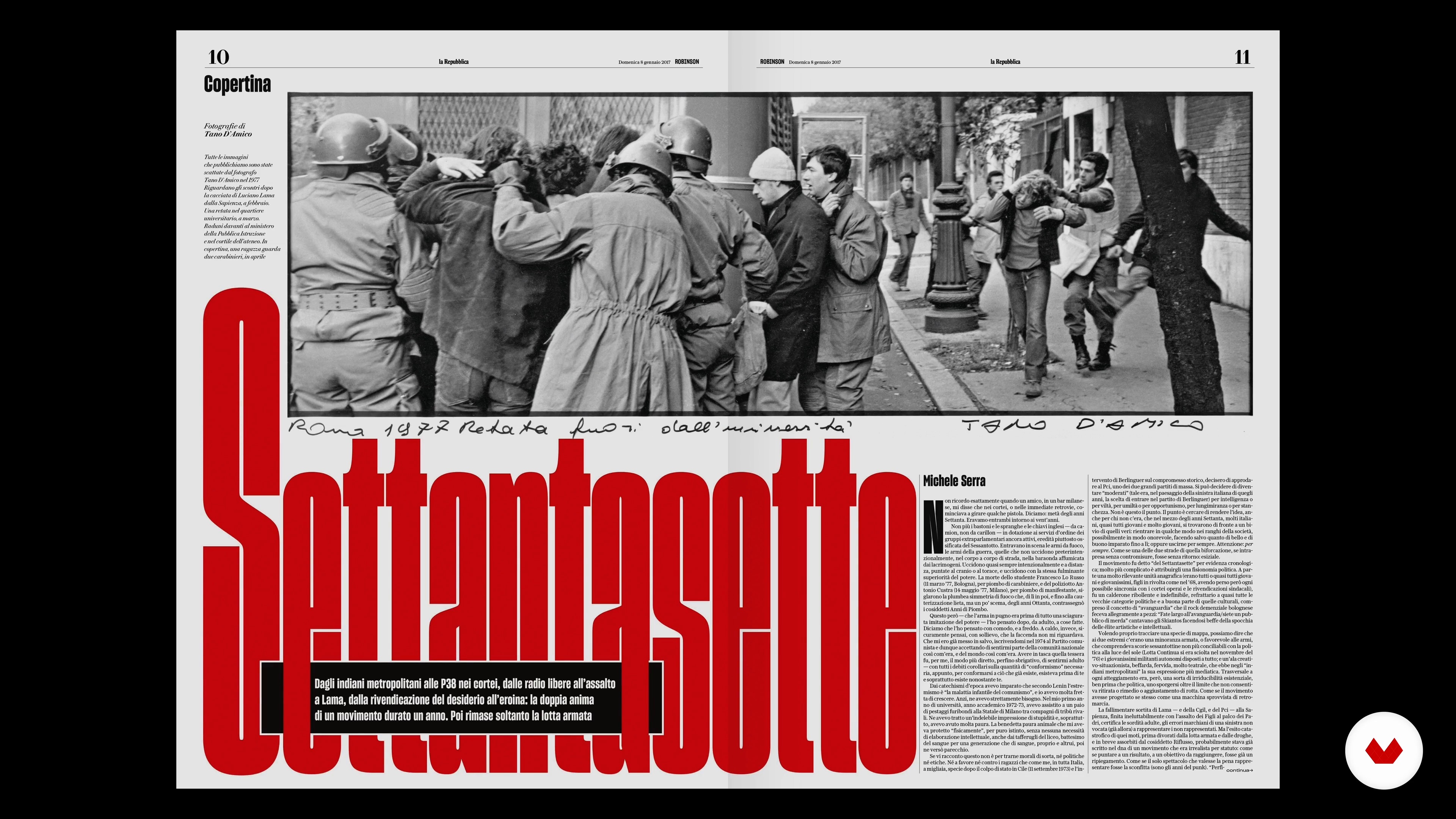
A tipografia
Sobre a videoaula: A tipografia
“Vamos nos concentrar na tipografia examinando diferentes tipos de fontes, tentando ver o que elas transmitem para entender os requisitos para a escolha de um tipo de letra específico. Entretanto, não é apenas a escolha que importa, mas como a tipografia é implementada em um projeto. Não são apenas as fontes usadas, mas como elas são usadas que definem o tom e a hierarquia das informações. A atenção aos detalhes tipográficos também significa rigor, cuidado e qualidade. Fatores que são fundamentais para uma marca de informação. A tipografia, portanto, deve representar a identidade de um jornal e o design gráfico deve fazer com que cada página e cada elemento sejam parte de um todo. Assim, quando você encontrar até mesmo um pequeno fragmento de uma página de jornal no chão, poderá saber imediatamente a qual cabeçalho ela pertence.”
“Agora vamos entrar no cerne do design e tentar entender quais são as ferramentas ou linguagens que nos ajudam a moldar nosso conteúdo. Vamos começar com o que é um dos princípios básicos, a tipografia. A tipografia é a base de tudo, de qualquer projeto que seja vídeo, seja digital, seja papel, seja jornal, que é um livro. A tipografia é o que dá identidade ao nosso jornal e, em todo o caso, dá-lhe a mesma tempo a sensação de valor, de prestígio. Assim como um jornalista cuida de um artigo nos mínimos detalhes, cuida das legendas, as palavras que são usadas nas escalas, o designer gráfico ta...”